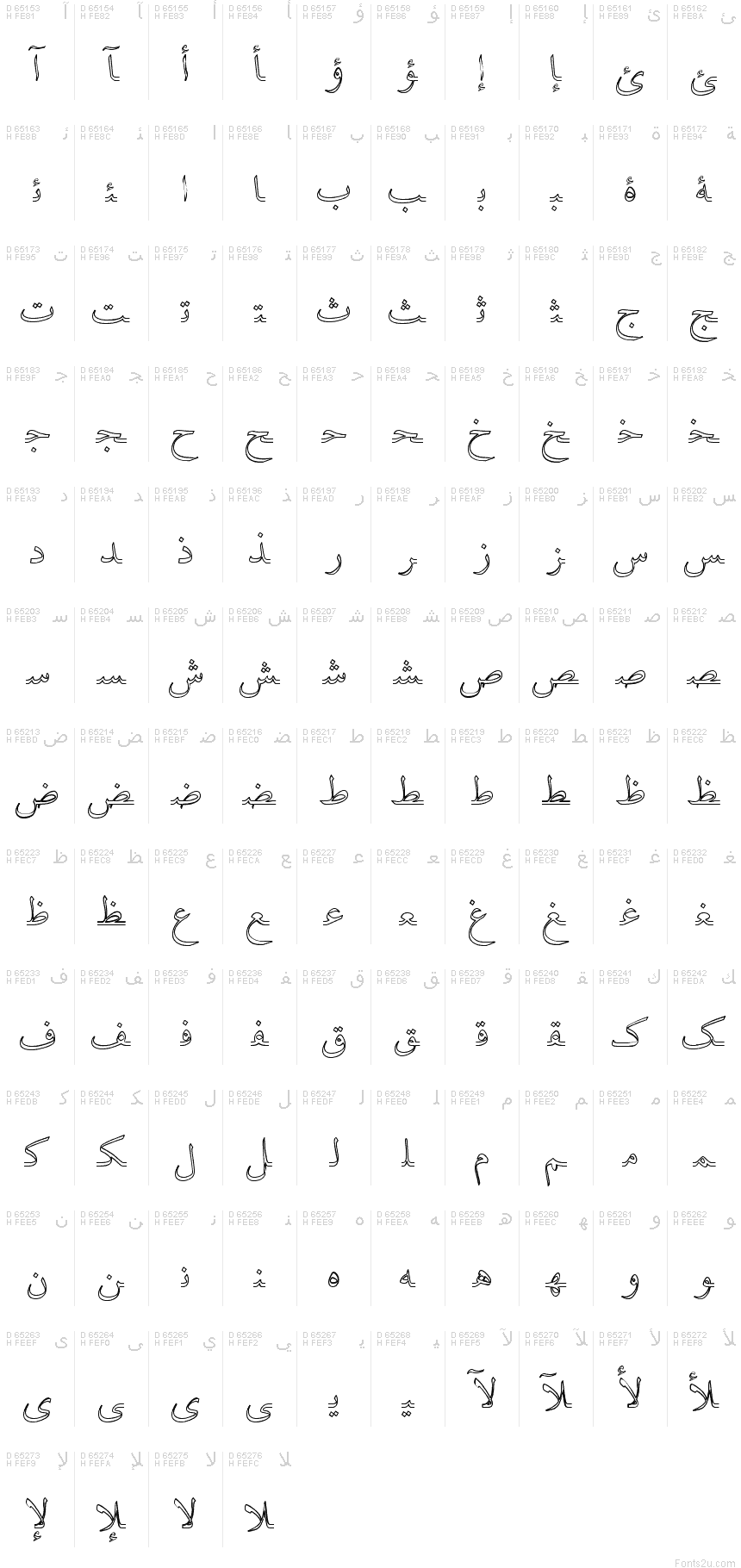
B Baran Outline od Borna Rayaneh je bezplatné arabské obrysové písmo definované zakrivenými zakončeniami v tvare háčikov, stúpajúcimi ťahmi a otvorenými kontúrami, vďaka čomu pôsobí na stránke ľahko. Dutý dizajn zachováva kaligrafický pohyb, pričom mu dodáva vzdušnejší a dekoratívnejší výraz, než aký by mal plný rez písma.
B Baran Outline sa skvele hodí na kultúrne plagáty, obálky kníh, jedálne lístky, obaly produktov či redakčnú grafiku – všade tam, kde toto bezplatné písmo dokáže orámovať krátky text bez toho, aby pôsobil ťažkopádne alebo blokovo. Obzvlášť presvedčivo vyzerá v titulkoch, na kartičkách a obálkach, pretože obrysové krivky ponechávajú okolo tvarov dostatok miesta a dodávajú krátkym slovám živý charakter.